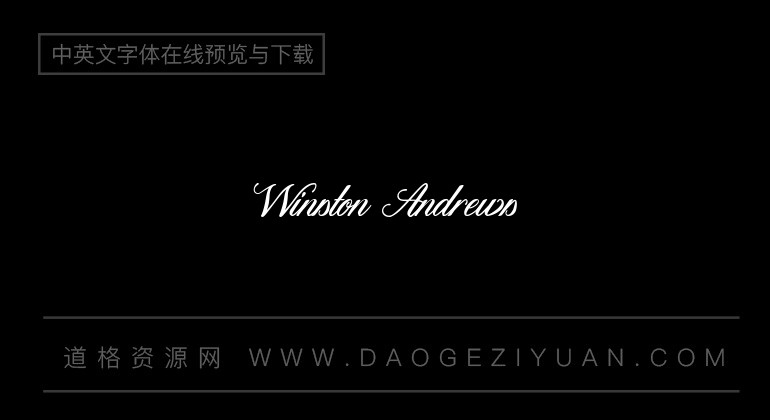
Winston Andrews 是一种非常流行的英文字体,它具有自然的外观,非常适合用于报纸、杂志和书籍的标题和正文。它的笔画细腻,字母间距适中,字体的粗细可以根据需要调整,使其具有更加舒适的视觉效果。它的字符结构也非常有趣,有助于增强文字的可读性。内容介绍
Winston Andrews是一款非常不错的手写艺术字体,具有很好的视觉感,适合于文化类的宣传设计、商业类品牌的广告和产品包装设计以及个性化文字排版等较多场景。